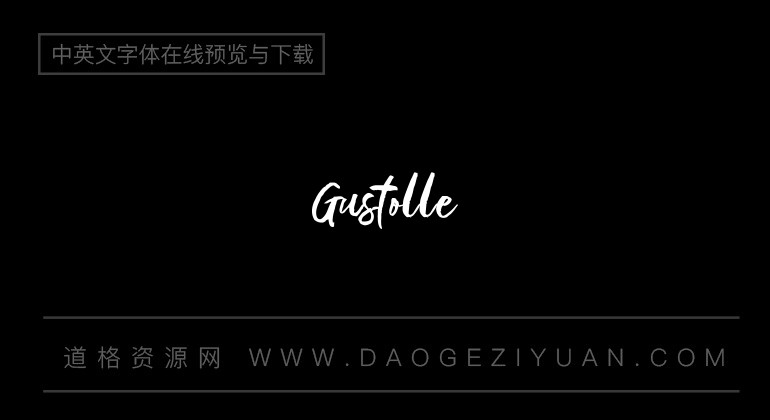
? Gustolle 字体是一款美式西餐风格的字体,具有浓厚的美式风情和轻松的曲线,可以让您的设计更加精致、优雅。它具有良好的可读性,可以用于报纸、杂志、网站、广告等设计中。它具有清晰、简洁的外观,可以提升您的设计的质感和气质。内容介绍
Gustolle是一款非常不错的手写艺术字体,具有很好的视觉感,适合于文化类的宣传设计、商业类品牌的广告和产品包装设计以及个性化文字排版等较多场景。